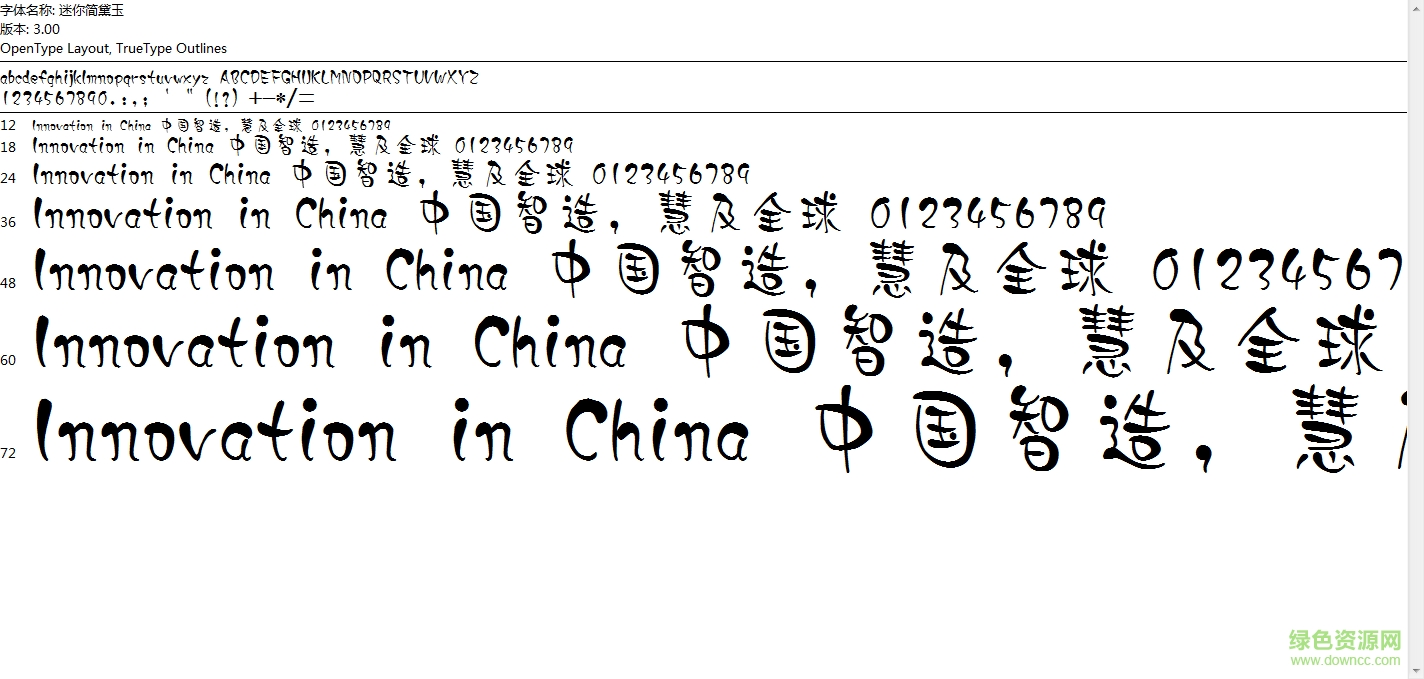
jdaiyu字體
jdaiyu是什么字體?jdaiyu字體又叫迷你簡黛玉,是一款弱柳扶風(fēng)的古風(fēng)字體,用在古風(fēng)海報(bào)、影視設(shè)計(jì)、創(chuàng)意設(shè)計(jì)等方面效果非常獨(dú)特,也能讓你所設(shè)計(jì)的東西更加具有特色,吸引到客戶們的注意力,喜歡改該字體的小伙伴快來本站下載吧!
jdaiyu字體介紹
一款別有風(fēng)范和神韻的字體,富有林妹妹清瘦的外形之美!字形圓滑亮麗,極具古典風(fēng)韻!
jdaiyu字體適用范圍
字體優(yōu)美清新,線條流暢,給人以華麗柔美之感,此種類型的字體,適用于女用化妝品、飾品、日常生活用品、服務(wù)業(yè)等主題。